Người dùng Canva thường gặp phải trường hợp lỗi phông chữ tiếng Việt khi sử dụng. Chúng khiến bạn loay hoay để làm sao chọn được kiểu chữ vừa đẹp vừa hỗ trợ tiếng Việt.
Bởi vậy, Gitiho ở đây để giúp bạn tiết kiệm thời gian thiết kế bằng cách tổng hợp 90+ font Việt hóa Canva phổ biến nhất.
Với kho dữ liệu khổng lồ bao gồm các kiểu chữ đa dạng, Canva mang đến những thiết kế mới mẻ, đầy tính sáng tạo và thú vị. Tuy nhiên, nhiều font chữ không hỗ trợ tiếng Việt khiến bạn khó khăn trong việc chỉnh sửa Text. Bởi vậy, chúng tôi đã tổng hợp file các mẫu chữ việt hóa trên Canva cho bạn.
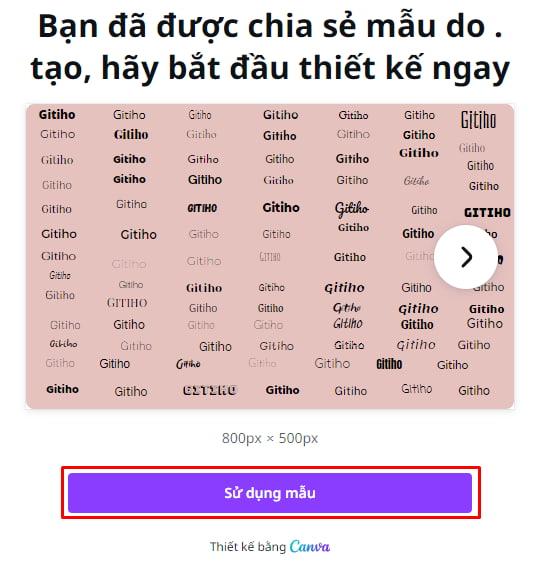
Bước 3: Tìm kiếm và chọn kiểu chữ mà bạn muốn sử dụng > Copy font chữ muốn sử dụng vào thiết kế của bạn.
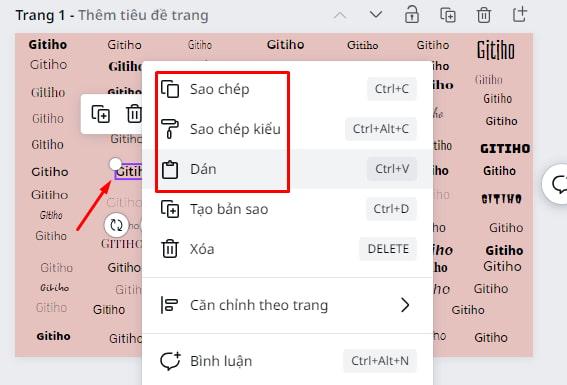
Vậy là đã hoàn thành các bước để sử dụng bộ font chữ Việt hóa đã được chúng tôi tổng hợp chi tiết. Giờ đây, bạn không cần phải mất nhiều thời gian tìm kiếm các font chữ mà Canva tiếng Việt hỗ trợ.
Nếu bạn sử dụng Canva thường xuyên, đôi khi bạn sẽ rất đau đầu vì chọn mãi không được kiểu chữ đã chuẩn Việt hóa. Tôi đã từng thay hết loại chữ này đến loại khác mà không tìm được phông chữ tiếng Việt Canva phù hợp.
Phông chữ chưa được Việt hóa sẽ khiến đoạn text của bạn bị lỗi. Các chữ cái có dấu (ví dụ: ồ, ớ, ừ, ạ,...) sẽ hiện một loại chữ khác so với kiểu bạn đầu.
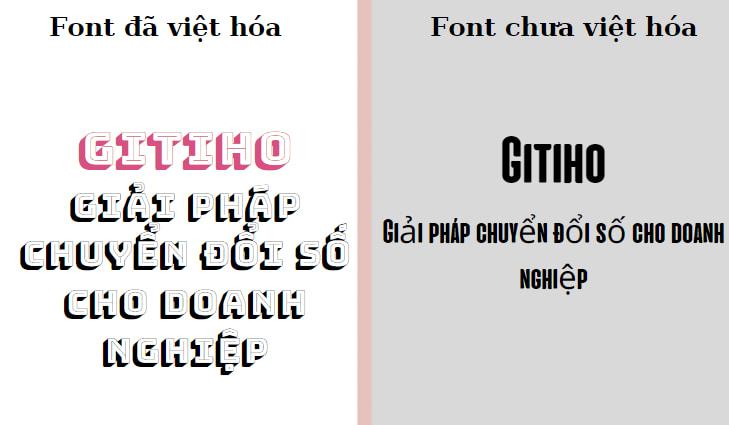
Bất cứ ai khi sử dụng tiếng Việt cho thiết kế trên Canva cần lưu ý đến những mẹo tìm kiếm font chữ Việt hóa này để không tốn nhiều thời gian:
Bước 1: Sử dụng từ khóa Sans Serif & Slab Serif khi tìm kiếm.
Serif mang nghĩa một đường thẳng hay một nét nhỏ ở trên mỗi chữ. Nó còn được biết đến với cái tên "chữ có chân" với đặc điểm chữ là những đường định hướng và ổn định cấu tạo chữ.
Sans serif là một phiên bản nâng cấp mang tính trẻ trung hơn. Các kiểu chữ này phù hợp với các thiết kế có tính sáng tạo, vui tươi hay các text được thiết kế cho trẻ em.
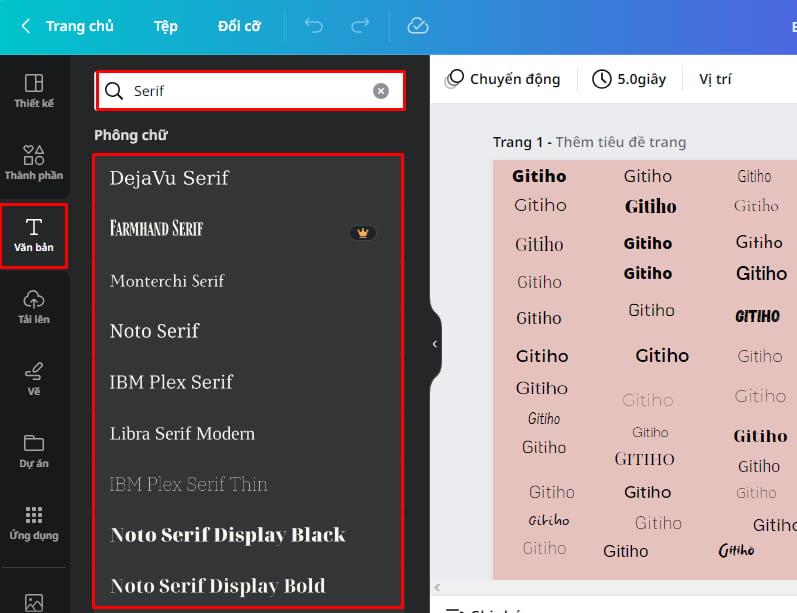
Bước 2: Chọn các loại font Việt hóa Canva có trong kết quả gợi ý để bắt đầu sử dụng.
Danh sách các phông chữ tiếng Việt này chắc chắn là chưa đủ, Bởi vậy, bạn hãy sử dụng mẹo tìm kiếm các font tiếng việt Canva hoặc file tổng hợp mà tôi đã liệt kê bên trên nhé.
Thiết kế của bạn sẽ trở lên chuyên nghiệp hơn: việc sử dụng font Việt hóa Canva giúp cho văn bản đồng nhất hơn. Nó mang lại tính thống nhất trong phong cách thiết kế giúp sản phẩm của bạn chuyên nghiệp.
Tạo nét độc đáo của riêng thương hiệu bạn: Việc cố gắng tìm kiếm các kiểu chữ Việt hóa đẹp trên Canva sẽ khiến thiết kế của bạn trở nên sống động hơn. Ngoài ra chọn đúng phông chữ còn làm nổi bật sự tương phản và hài hòa giữa các thành phần trong thiết kế.
Giúp truyền tải thông điệp của bạn: Sử dụng nét chữ nghiêng mềm mại hay nét thẳng cứng rắn phần nào giúp người xem cảm nhận được ý định của người thiết kế. Tùy vào mục đích thiết kế mà chúng ta nên chọn phông chữ tiếng Việt phù hợp.